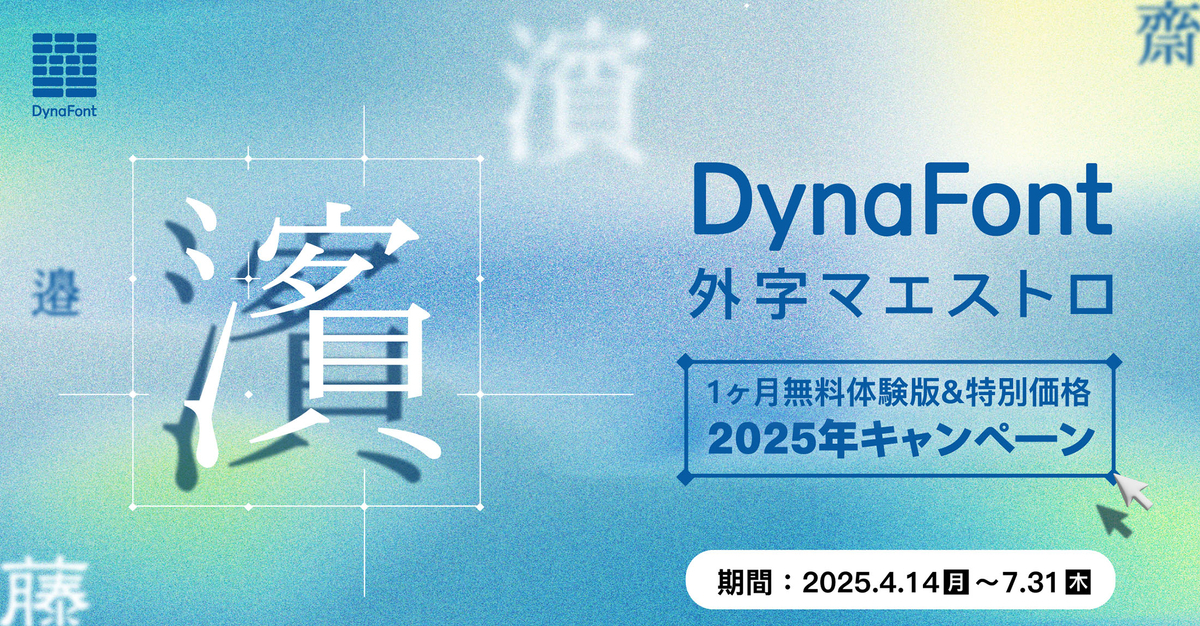
PCで表示されない特殊な文字問題を解決!外字4,901文字対応のダイナフォント19書体を使用可能の「DynaFont外字マエストロ」を無料でお試し&お得に買える2025年キャンペーンを4月14日から開催
ダイナコムウェアは、2025年4月14日(月)から7月31日(木)の期間中、外字フォント年間ライセンス「DynaFont外字マエストロ」の1ヶ月無料体験版および特別価格になる2025年キャンペーンを開催した。
「DynaFont外字マエストロ」は4,718文字の外字に183種類の案内用図記号(ピクトグラム)を収録した合計外字4,901文字対応のダイナフォント19書体を使用でき、外字も作成可能な常に最新の外字フォント環境が行き渡る外字フォント年間ライセンス製品。
DynaFont外字マエストロで最新の外字環境を構築しよう
「DynaFont外字マエストロ」には、常に最新の外字環境を構築していただくための豊富な外字収録をはじめ、様々な特徴を兼ね備えている。
DynaFont外字マエストロ特徴その1「ピクトグラム」を含む4,901文字の外字が使い放題
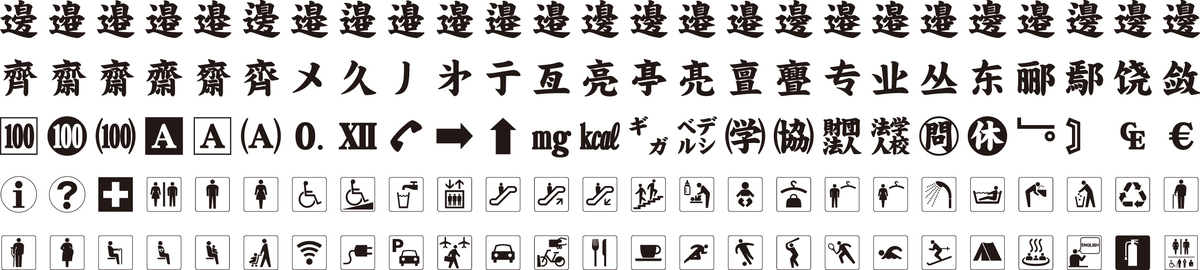
法務省指定となる人名用漢字を全て網羅し、各自治体で採用されている人名外字など使用頻度の高い人名外字3,296文字を厳選して収録しており、名簿作成での正しい人名表記や、はがきソフトなどでの宛名書きなど様々な場面で使用できる。
さらにBiblos記号外字1,395文字、貨幣外字27文字に加え、日本で開催される国際的なイベントやインバウンド需要を受けて更に需要が高まるピクトグラム(案内用図記号)183種類も収録し、合計4,901文字の外字を収録している。国籍を問わず分かりやすいピクトグラムはグローバル化社会を推進するための円滑で移動しやすい環境整備の実現に貢献する。
DynaFont外字マエストロ特徴その2 外字対応「超極太楷書体」を新たに収録した厳選19書体が使い放題
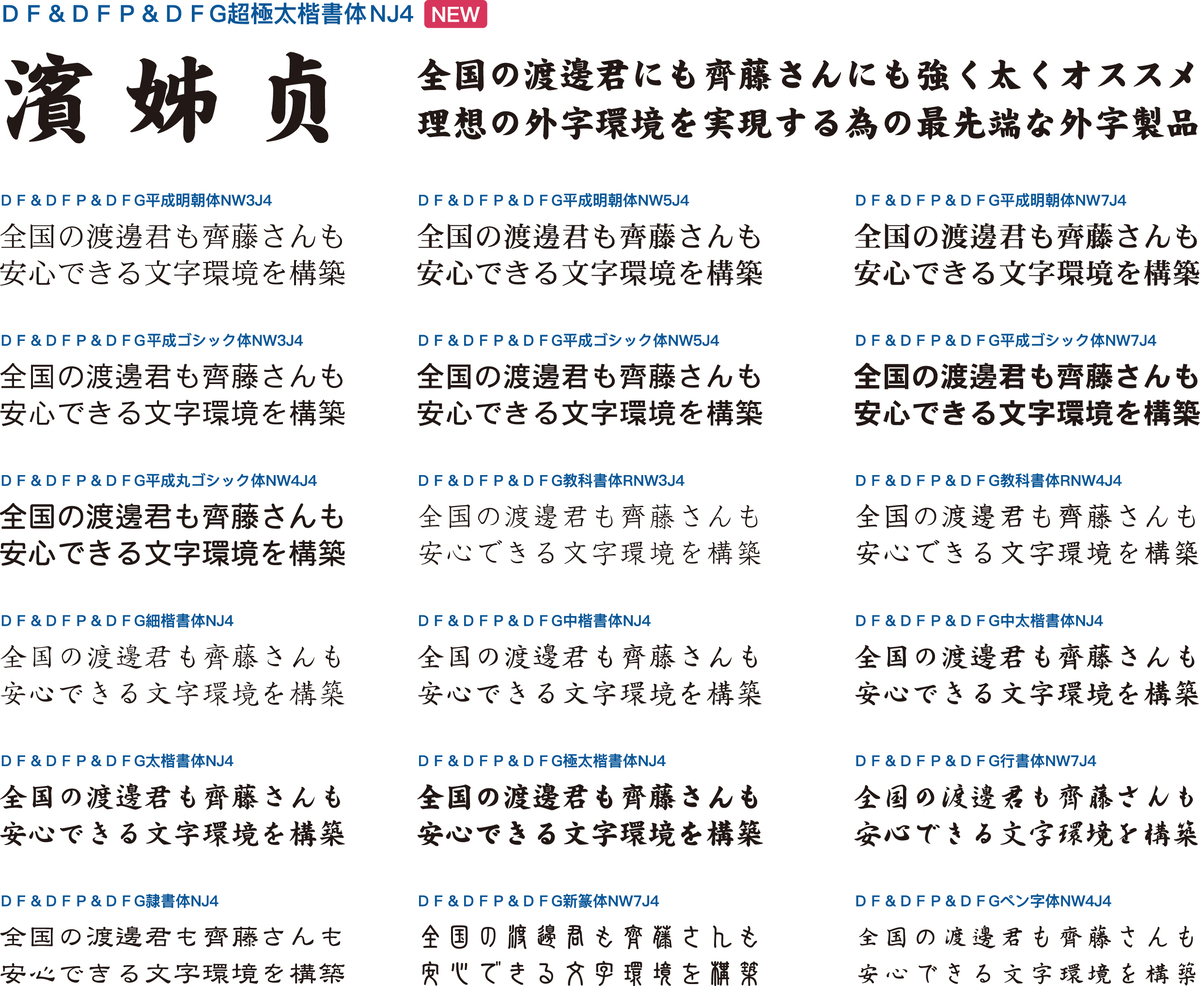
「DynaFont外字マエストロ」ではダイナコムウェアのこれまでの外字対応フォント製品に加え、新たに「超極太楷書体」を外字対応書体の新書体として収録し、外字対応19書体を使用できる。さらに、今後も最新書体および最新外字が随時追加されていき、ユーザーには常に最新の外字フォント環境が行き渡る。
DynaFont外字マエストロ特徴その3 足りない外字も「外字作成ツール」で簡単、キレイに作り放題!!
Windows OS環境では「DynaFont外字マエストロ」に収録されていない特殊な文字を使用したい場合『外字作成ツール』を使用して簡単な操作で綺麗な外字が作成できる。「DynaFont外字マエストロ」収録19書体の既存の漢字から一筆(ストローク)単位でパーツを取り出すことができる。また取り出したパーツを他の漢字や一筆と組み合わせることで迅速かつ簡単に外字が作成できる。約300種類におよぶ豊富なストロークを搭載しており、ストローク同士の組み合わせや他の漢字の一部と組み合わせることで無限に近い数の外字の作成が可能。